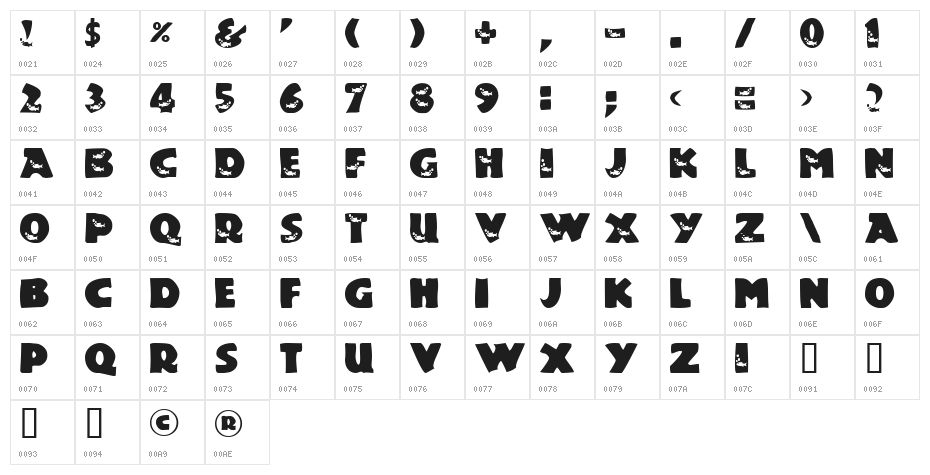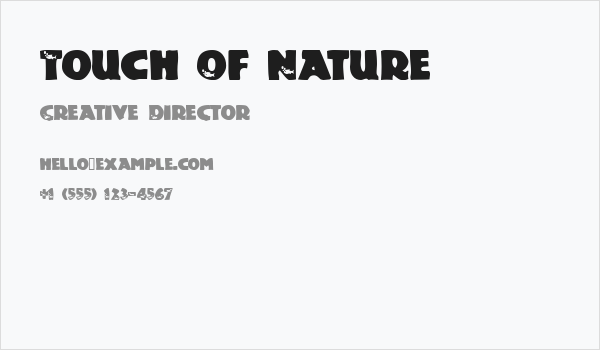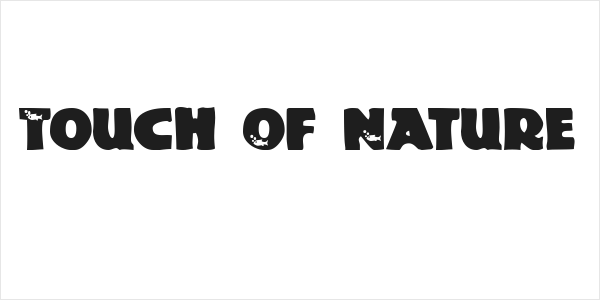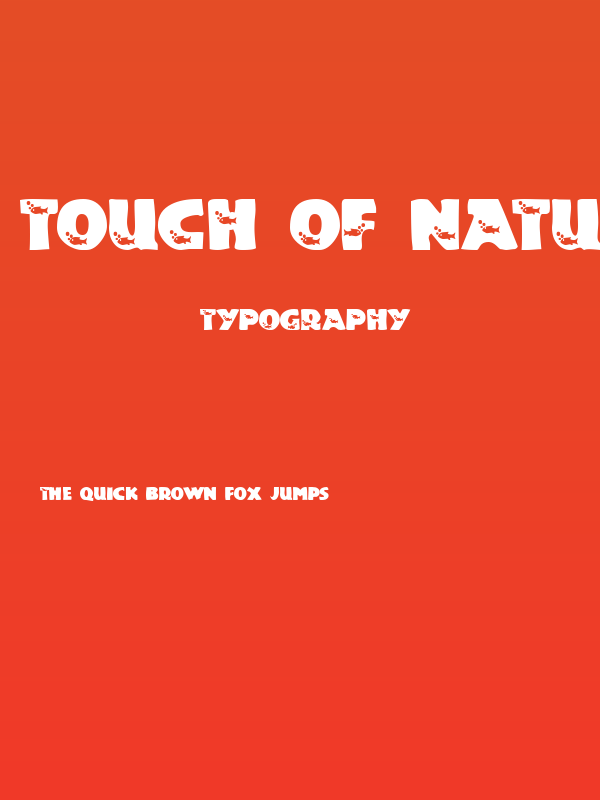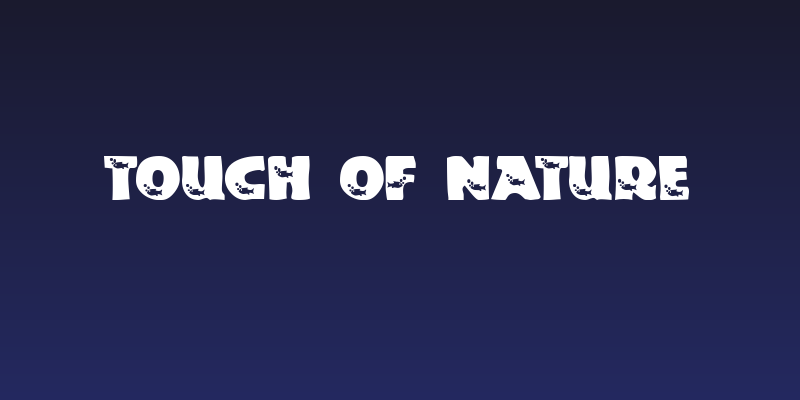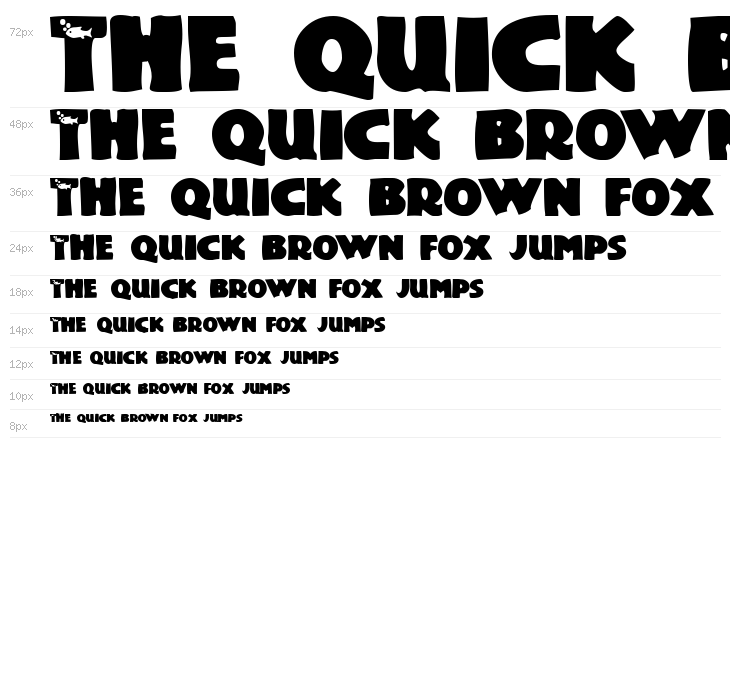
Touch Of Nature Font
| Categorie | Broken |
| Progetti proposti | Ideal for eco-friendly branding, outdoor event posters, children's book covers, and nature-themed merchandise. |